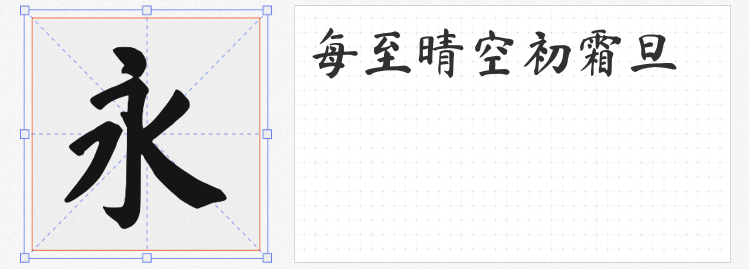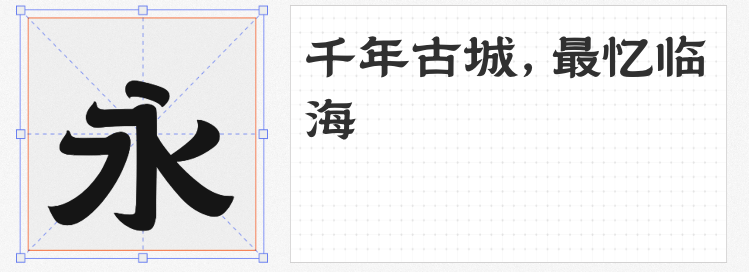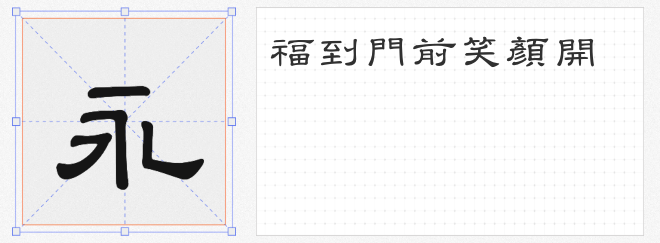
元旦将至,设计一张吸睛的海报至关重要,而字体的选择则是海报的灵魂所在。以下四款免费商用字体,兼具文化底蕴与艺术美感,定能为你的元旦海报设计增添独特魅力。
玄冬楷书基于开源字体《马善政毛笔楷书》拓展而成,修复了原版88处错误字形,并新增竖排排版特性。其字形端庄稳重,笔画粗细均匀,起笔收笔间尽显楷书的严谨与规范。在元旦海报设计中,若想营造出庄重、正式的氛围,玄冬楷书是不二之选。
台湾教育部标准隶书依据《教育部隶书母稿》制成,收录4808个常用汉字,是台湾中文的规范依据。它完整保留了传统隶书“蚕头燕尾”“一波三折”的经典笔法,笔画粗细变化自然流畅,整体风格古朴庄重。在元旦海报设计中,这款字体适合用于传递正式、严肃的信息,如活动的时间、地点等。其规范的字形和独特的艺术风格,能让海报在众多设计中脱颖而出。
临海隶书结合了临海城市特质和隶书体,将千年古城、人文繁盛、山水之韵等展示得淋漓尽致。其字形古朴内敛,充满厚重、古典和拙朴的特质。在元旦海报设计中,使用临海隶书可以赋予海报独特的地域文化气息,让观众在欣赏海报的同时,也能感受到临海这座城市的独特魅力。
演示佛系体由80岁书法家纪国才先生手稿创作,看似随意却蕴含着老先生一生的阅历和经验。其笔画独立分明,落笔力度均匀,字形灵感源自小篆,却更注重美学表达。在元旦海报设计中,若想营造出轻松、愉悦的氛围,演示佛系体是绝佳选择。它能为海报增添一份随性与洒脱,让观众在忙碌的节日氛围中感受到一丝宁静与惬意。